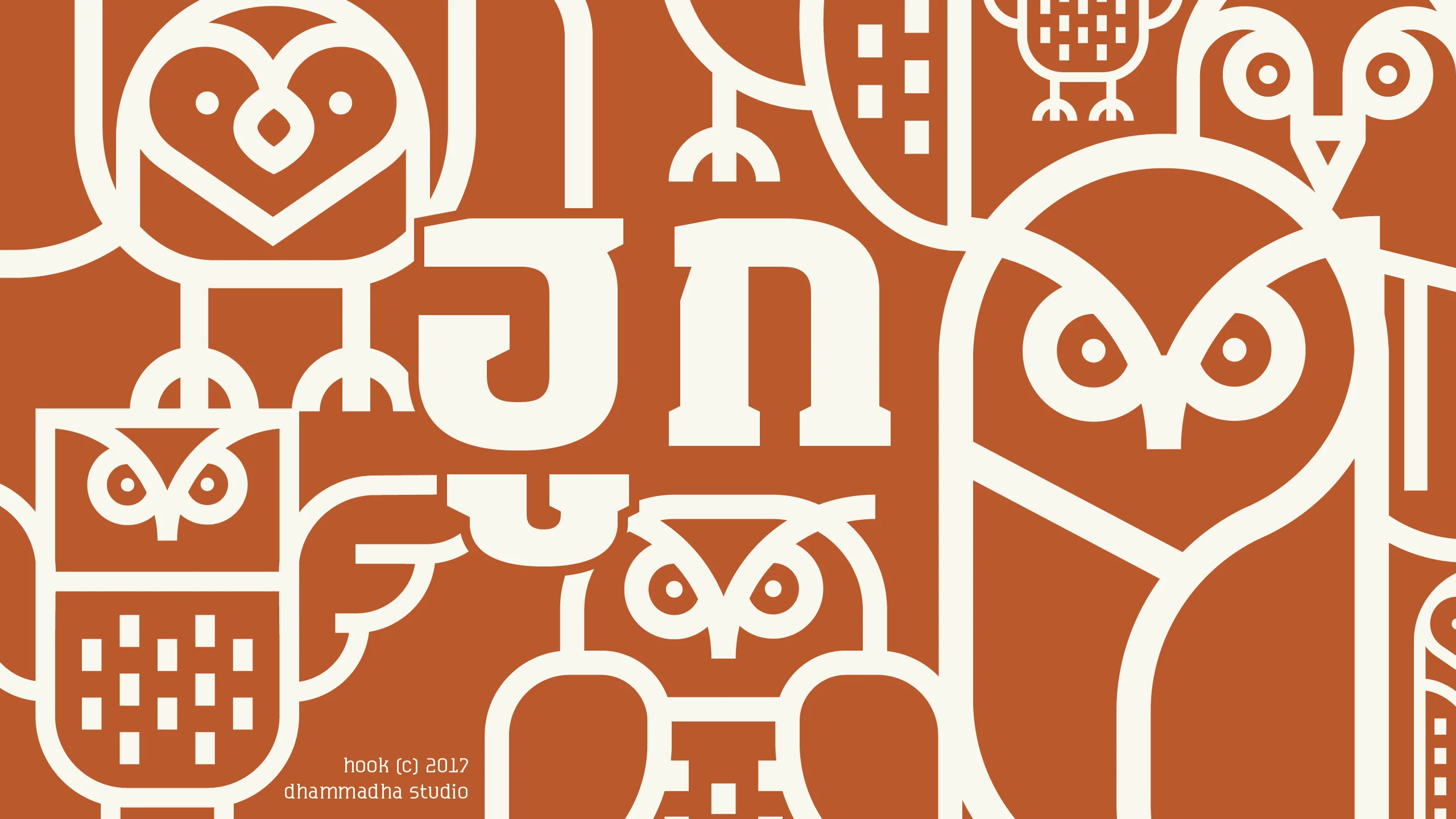
"ฮูก | hook" คือผลงานที่ต่อยอดมาจากแบบร่างอักษรในโปรเจกต์เชิงคอนเซปต์ ที่มุ่งเน้นการใช้ตัวอักษรไทยเป็นหัวใจหลักในการสร้างสรรค์สื่อภาพ โดยจุดเด่นของฟอนต์ชุดนี้เกิดจากความลุ่มลึกในความหมายของการเขียนทับศัพท์ ซึ่งมอบมุมมองที่แตกต่างและทับซ้อนกันระหว่างสองภาษา กลายเป็นที่มาของชื่อ 'ฮูก' ที่เชื่อมโยงความหมายอันหลากหลายเข้าไว้ด้วยกันอย่างมีเสน่ห์ สะท้อนถึงความคิดสร้างสรรค์ที่เกิดจากความช่างสังเกตและการตีความใหม่ที่ฉีกออกจากกรอบเดิมๆ นอกจากเรื่องราวเบื้องหลังที่น่าสนใจ ฟอนต์ชุดนี้ยังถูกพัฒนาขึ้นเพื่อรองรับการใช้งานระดับอาชีพอย่างเต็มรูปแบบ โดยบรรจุชุดอักษรมาให้ถึง 5 น้ำหนัก (Weights) พร้อมด้วยตัวเอียง (Italics) ที่ช่วยเพิ่มจังหวะและมิติให้กับงานออกแบบ ไม่ว่าจะเป็นงานสร้างสรรค์ภาพลักษณ์แบรนด์ที่ต้องการความหมายลึกซึ้ง หรือการจัดวางตัวอักษรในงานกราฟิกที่เน้นความเฉียบคม "ฮูก | hook" จะช่วยเปิดความเป็นไปได้ใหม่ๆ ให้กับผลงานของคุณ และทำให้ทุกการสื่อสารดูมีเรื่องราวที่น่าติดตาม